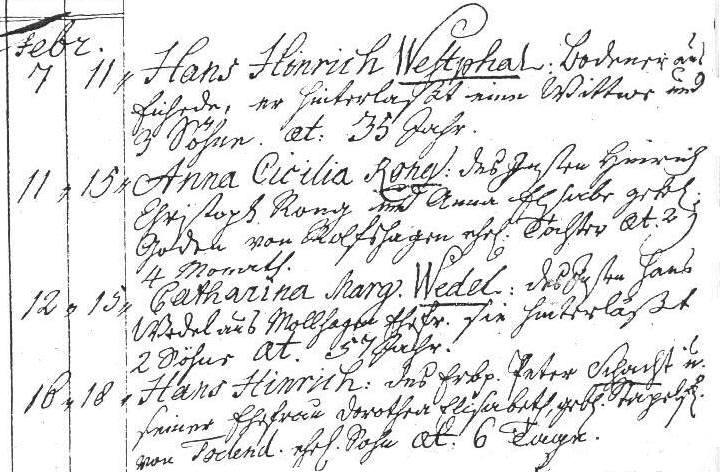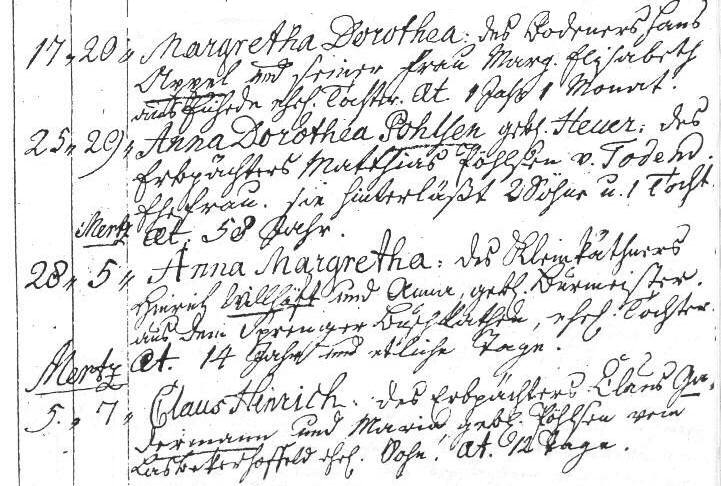
Dies ist ein Sterberegister, links der Tag des Todes, rechts der Tag der Beerdigung. Leseübungen: ein Kirchenbuch von 1784
A church book of 1784
Personennamen wurden in lateinischer Schrift geschrieben.
Hinter "geb." folgt stets ein Kringel als Zeichen für eine Abkürzung.
Hans Heinrich Westphal : Bodener (= Bödner) aus
Eichede, er hinterlaßt eine Wittwe und
3 Söhne. aet (= Alter) 35 Jahr
Anna Cicilia Rong : des Insten (= etwa ein Tagelöhner) Hinrich
Christoph Rong und Anna Elsabe geb.
Goden von Rolfshagen ehel. Tochter aet 2 J
4 Monath
Catharina Marg. Wedel : des Insten Hans
Wedel aus Mollhagen Ehefr. sie hinterläßt
2 Söhne aet. 57 Jahr
Hans Hinrich : des Erbp. (= Erbpächters) Peter Schacht u.
seiner Ehefrau Dorothea Elisabeth, geb. Stapelf. (= Stapelfeld)
von Todend. (= Todendorf) ehel. Sohn aet. 6 Tage
Margretha Dorothea : des Bodeners Hans
Appel und seiner Frau Marg. Elisabeth
aus Eichede ehel. Tochter. aet. 1 Jahr 1 Monat
Anna Dorothea Pohlsen (=Pöhlsen) geb. Heuer, des
Erbpächters Matthias Pöhlsen v. Todend.
Ehefrau. sie hinterläßt 2 Söhne u. 1 Tocht.
aet. 58 Jahr
Anna Margaretha : des Kleinkäthners
Hinrich Willhöft und Anna geb. Burmeister
aus dem Sprenger Buschkathen , ehel. Tochter
aet. 14 Jahre und etliche Tage
Claus Hinrich : des Erbpächters Claus Ga-
dermann und Maria geb. Pöhlsen vom
Lasbekerhoffeld (= Lasbeker Hoffeld) ehel. Sohn. aet. 12 Tage